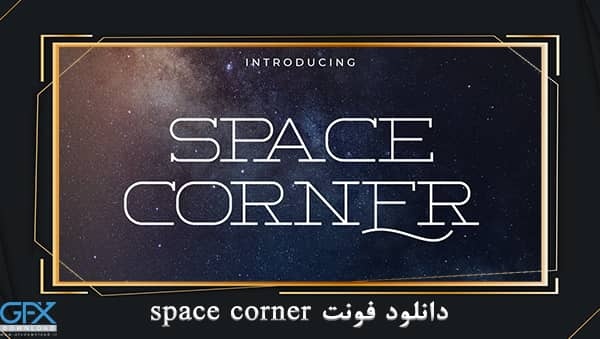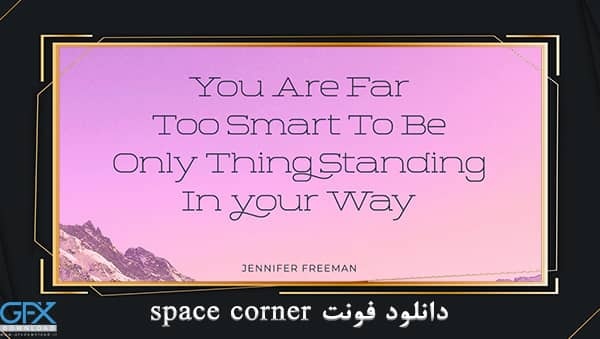
فونت انگلیسی نازک Space Corner
فونت بسیار نازک و خطی انگلیسی  Space Corner
دانلود فونت نازک و زیبای انگلیسی Space Corner
Space Corner یک فونت serif بسیار نازک و زیبا است. این حروف با ترتیب حروف زیبا ، در طرح های رسمی و غیر رسمی برجسته به نظر می رسند. ایده آل برای سرفصل ها یا لوگوها ، پوستر ، موضوع آینده نگرانه ، و غیره. متن الهام بخش خود را در سبک حروف چاپی مدرن با استفاده از فونت انگلیسی نازک Space Corner ایجاد کنید.